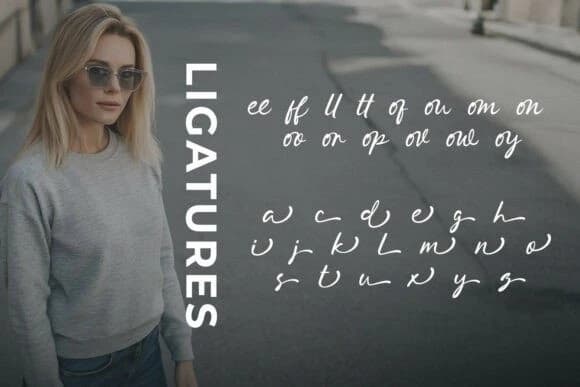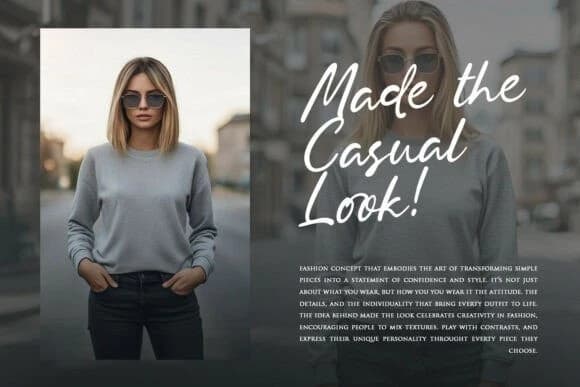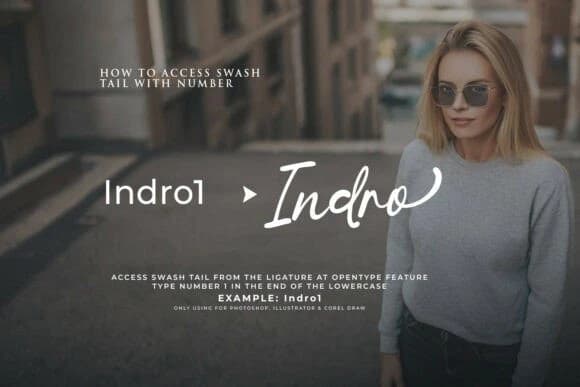
Blesh Forte Font
Blesh Forte Font, doğal bir fırça etkisine sahip bir el yazısı stili fontudur ve gerçek el yazısının güzelliğini yakalamak için tasarlanmıştır. Her çizgi canlı hissedilir — akıcı, ifade dolu ve kişiliğiyle dolu. Bu font, otantik bir el yazısı cazibesi sunar ve tasarımlarınıza sıcak, şık ve yüksek ka
Blesh Forte Font, gerçek el yazısının güzelliğini yakalamak için tasarlanmış, doğal bir fırça etkisine sahip bir el yazısı fontudur. Her bir vuruş canlı hissedilir — pürüzsüz, ifadeli ve karakter dolu. Otantik bir el yazısı cazibesi sunar ve tasarımlarınıza sıcak, şık ve premium bir hava katar.
Blesh Forte